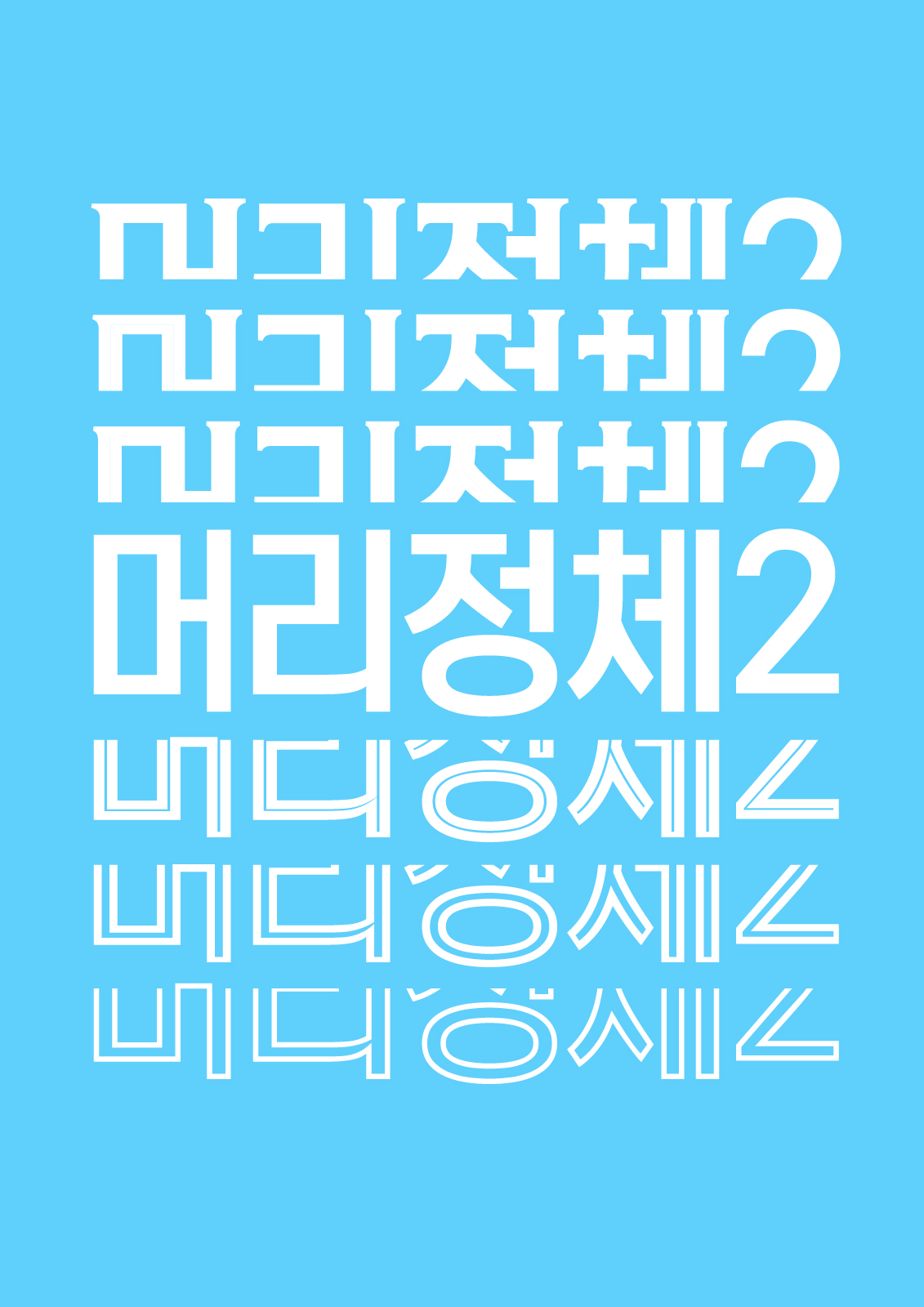
Yoon 머리정체2 Variable
Variable 폰트, 우리 말로 가변 폰트라 합니다. 고딕, 인라인, 세리프 등 폰트 스타일은 물론 폰트의 선, 면의 컬러까지. 사용자가 직접 변형하여 쓸 수 있는 DIY 폰트이지요. 느껴보세요. 디테일을 내 맘대로 조정하며 내게 딱 맞는 느낌을 연출하는 기쁨. 머리정체2 Variable과 함께라면 누구나 폰트 디자이너랍니다.